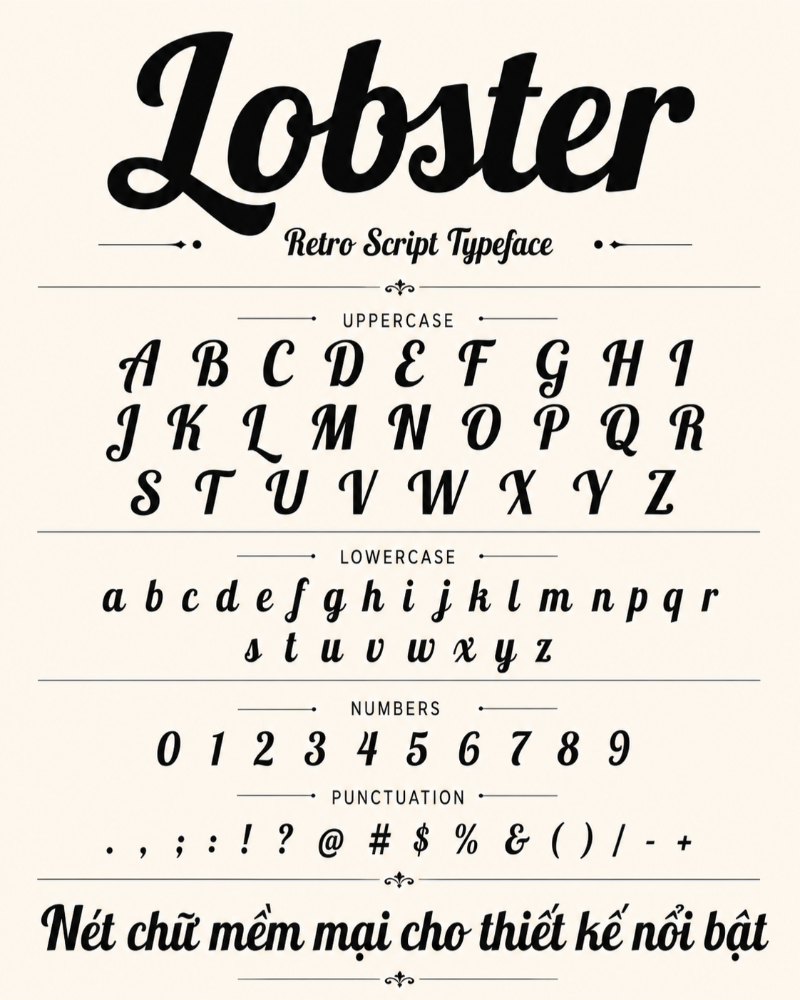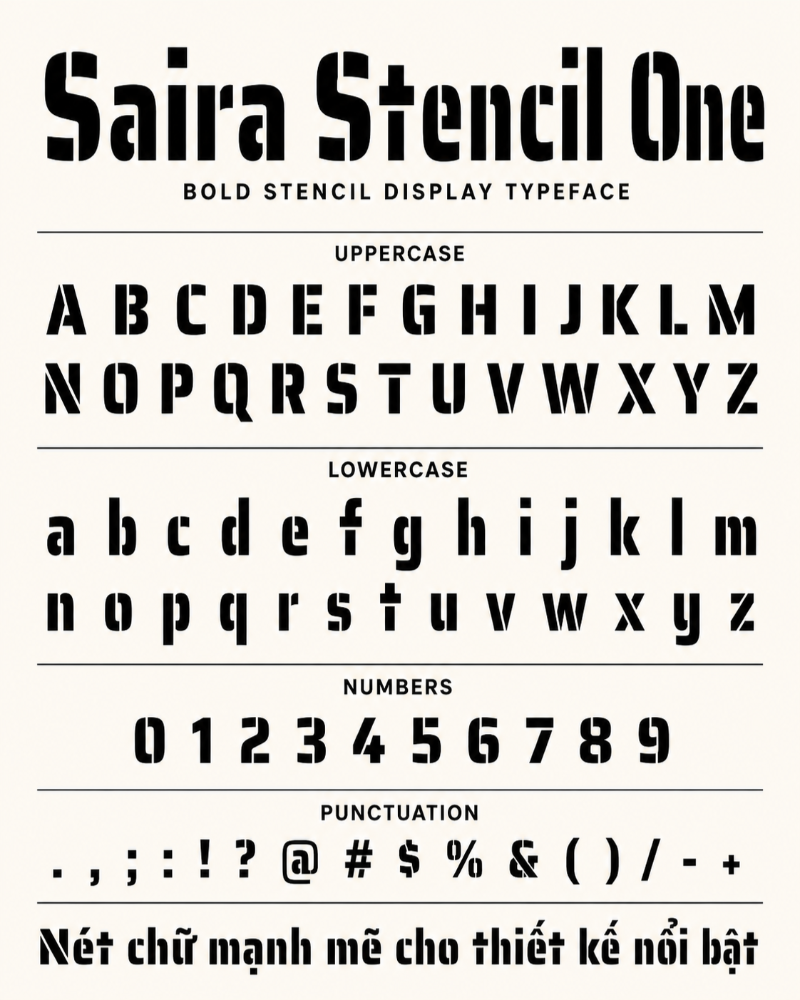
Khi đọc tin tức, lướt mạng xã hội hoặc xem một mẫu banner quảng cáo, yếu tố nào khiến bạn dừng lại lâu hơn? Có thể là hình ảnh bắt mắt, màu sắc nổi bật hoặc một câu thông điệp ấn tượng. Tuy nhiên, thứ thường gây chú ý đầu tiên chính là tiêu đề. Một font chữ tiêu đề đẹp không chỉ làm nội dung nổi bật hơn mà còn giúp thể hiện cá tính, cảm xúc và phong cách riêng của thương hiệu.
Trong bài viết này, In Đại Minh sẽ chia sẻ đến các bạn hơn 12 font chữ tiêu đề đẹp, đã hỗ trợ tiếng Việt, kèm theo những gợi ý ứng dụng thực tế để thiết kế của bạn trông chuyên nghiệp và cuốn hút hơn.
Tại sao một font chữ tiêu đề đẹp lại quan trọng?
Nhiều người mới làm thiết kế thường chọn một font duy nhất cho cả tiêu đề và phần nội dung. Cách làm này có thể khiến bố cục thiếu điểm nhấn, kém chuyên nghiệp và khó thu hút người xem. Thực tế, font tiêu đề đóng vai trò rất lớn trong việc tạo ấn tượng ban đầu.
- Tiêu đề là điểm chạm đầu tiên với người xem: Trong vài giây đầu tiên, người đọc thường nhìn vào tiêu đề trước khi quyết định có tiếp tục xem nội dung hay không. Vì vậy, một font chữ tiêu đề nổi bật sẽ giúp thiết kế gây chú ý nhanh hơn, giữ chân người xem tốt hơn và tăng khả năng truyền tải thông điệp.
- Font tiêu đề và font nội dung có vai trò khác nhau: Font tiêu đề, hay còn gọi là Display Font, cần có cá tính rõ ràng, độ nổi bật cao và khả năng tạo ấn tượng mạnh. Trong khi đó, font dùng cho nội dung chính nên đơn giản, dễ đọc và thoải mái cho mắt khi đọc lâu. Nếu dùng sai vai trò, thiết kế dễ bị rối hoặc thiếu sức hút.
- Font chữ ảnh hưởng đến cảm xúc và nhận diện thương hiệu: Mỗi kiểu chữ đều mang một sắc thái riêng. Font có chân thường tạo cảm giác sang trọng, cổ điển và đáng tin cậy. Font không chân đem lại vẻ hiện đại, gọn gàng và chuyên nghiệp. Còn font viết tay thường gợi sự mềm mại, sáng tạo và giàu cảm xúc. Chọn đúng font tiêu đề sẽ giúp thiết kế truyền tải đúng tinh thần mà thương hiệu hoặc nội dung muốn thể hiện.
Top 12+ font chữ tiêu đề đẹp, việt hóa cho thiết kế 2026
Để bạn dễ chọn font phù hợp với từng kiểu thiết kế, danh sách dưới đây được chia theo phong cách sử dụng và nhóm ngành phổ biến. Mỗi font đều có cá tính riêng, phù hợp cho tiêu đề, banner, poster, bìa tạp chí hoặc các ấn phẩm nhận diện thương hiệu.
Playfair Display
Playfair Display là một font Serif có chân nổi bật, gây ấn tượng nhờ sự tương phản rõ giữa nét mảnh và nét dày. Kiểu chữ này mang lại cảm giác sang trọng, tinh tế và có phần quyền quý. Đây là lựa chọn rất phù hợp cho tiêu đề tạp chí thời trang, banner mỹ phẩm, thương hiệu cao cấp hoặc các thiết kế cần vẻ đẹp thanh lịch.
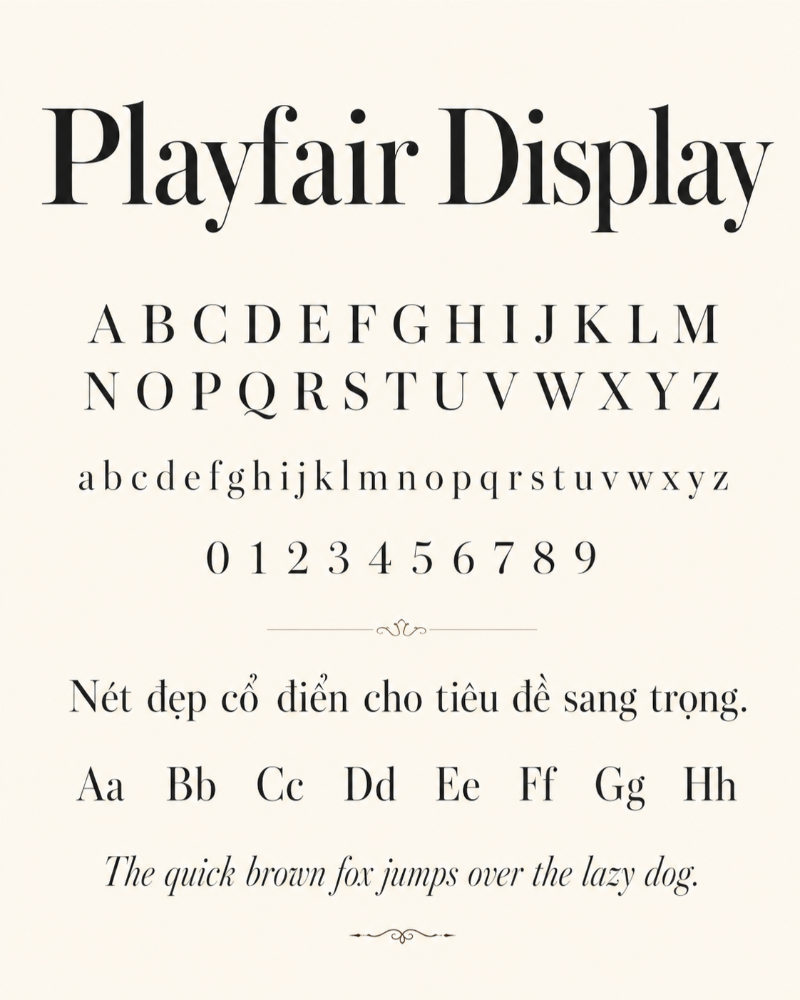
Prata hoặc Yeseva One
Prata và Yeseva One cũng thuộc nhóm font có chân, nhưng đường nét mềm mại và giàu cảm xúc hơn. Hai font này tạo cảm giác nữ tính, trang nhã và quyến rũ, rất hợp với các thiết kế về làm đẹp, spa, thời trang, thiệp cưới hoặc dịch vụ wedding planner. Nếu bạn muốn tiêu đề vừa nổi bật vừa có nét duyên dáng, đây là nhóm font đáng cân nhắc.
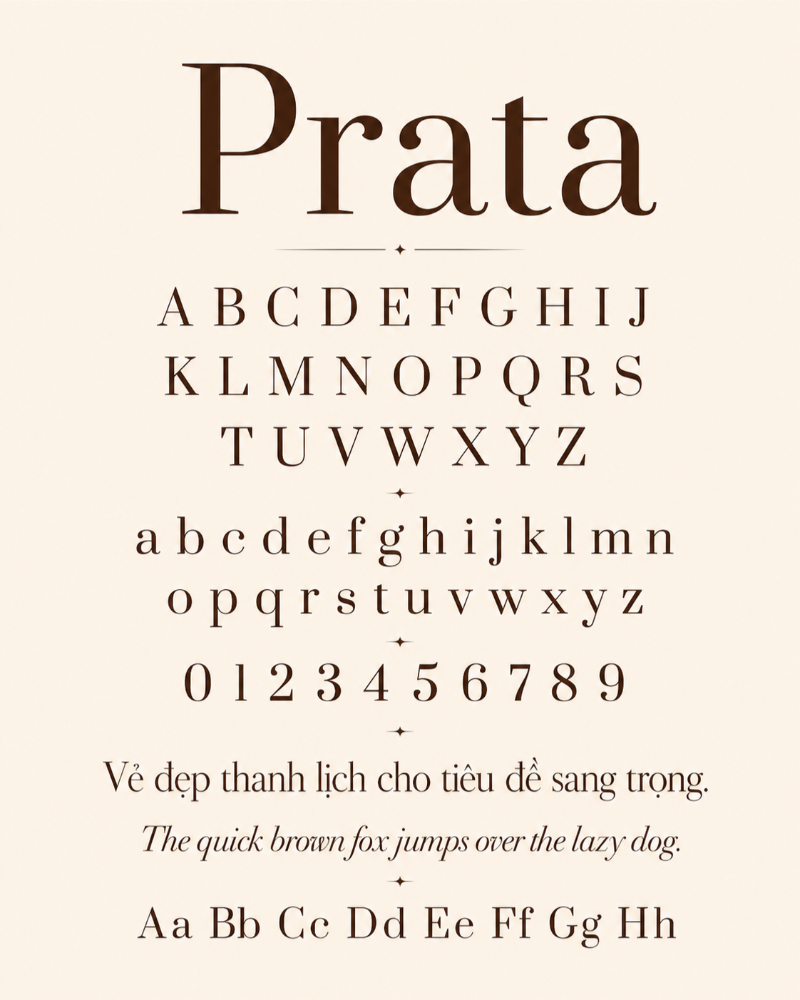
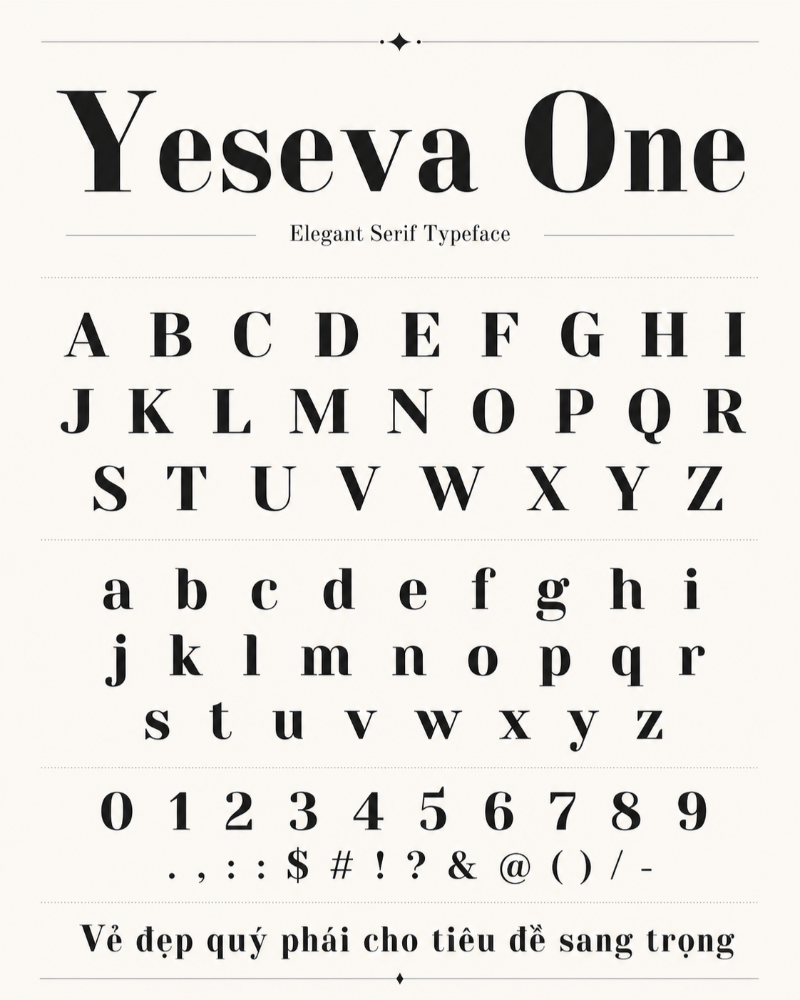
Charmonman
Charmonman mang phong cách thư pháp phương Tây, lấy cảm hứng từ nét chữ viết tay cổ điển. Font này có đường nét bay bổng, mềm mại nhưng không quá rườm rà hay sến. Nhờ vẻ thanh lịch và trang trọng, Charmonman thường được dùng cho thiệp mời, poster sự kiện cao cấp, thiết kế cưới hỏi hoặc các ấn phẩm cần tạo cảm giác tinh tế ngay từ phần tiêu đề.
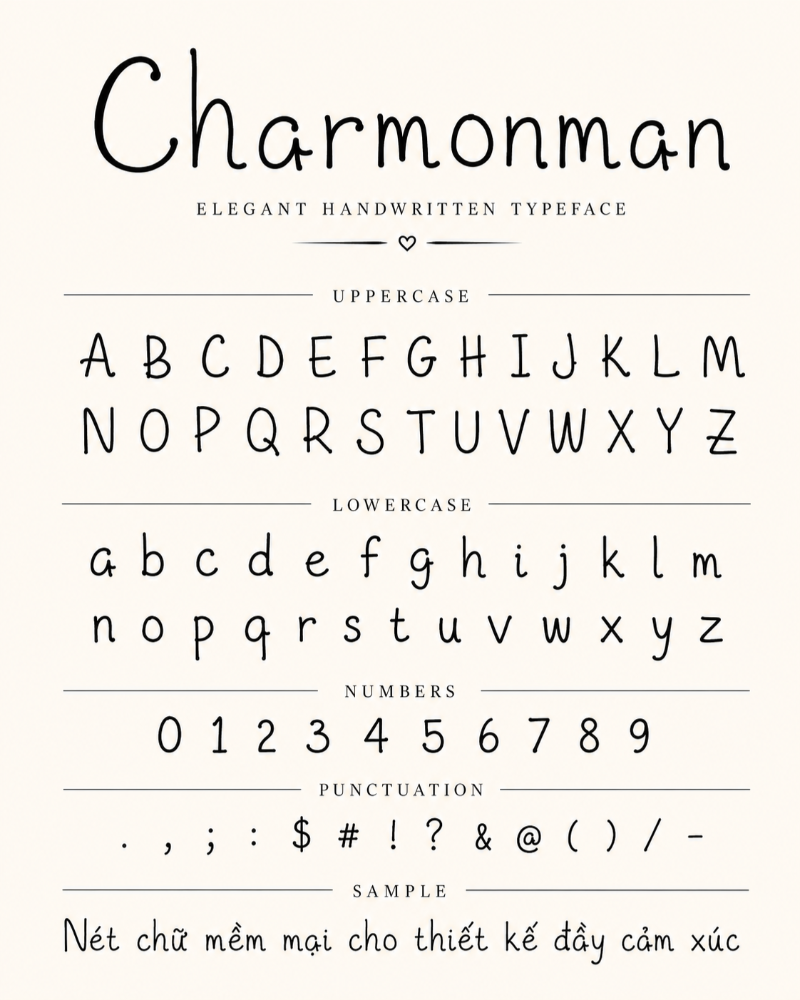
Montserrat Black hoặc ExtraBold
Montserrat được xây dựng dựa trên các đường nét hình học chắc chắn, bố cục chữ rõ ràng và khoảng cách ký tự thoáng. Khi dùng bản Black hoặc ExtraBold, font này tạo cảm giác mạnh mẽ, hiện đại và đáng tin cậy. Đây là một trong những font chữ quen thuộc nhất trong thiết kế UI/UX, nhận diện thương hiệu, logo doanh nghiệp và các tiêu đề cần sự chuyên nghiệp.
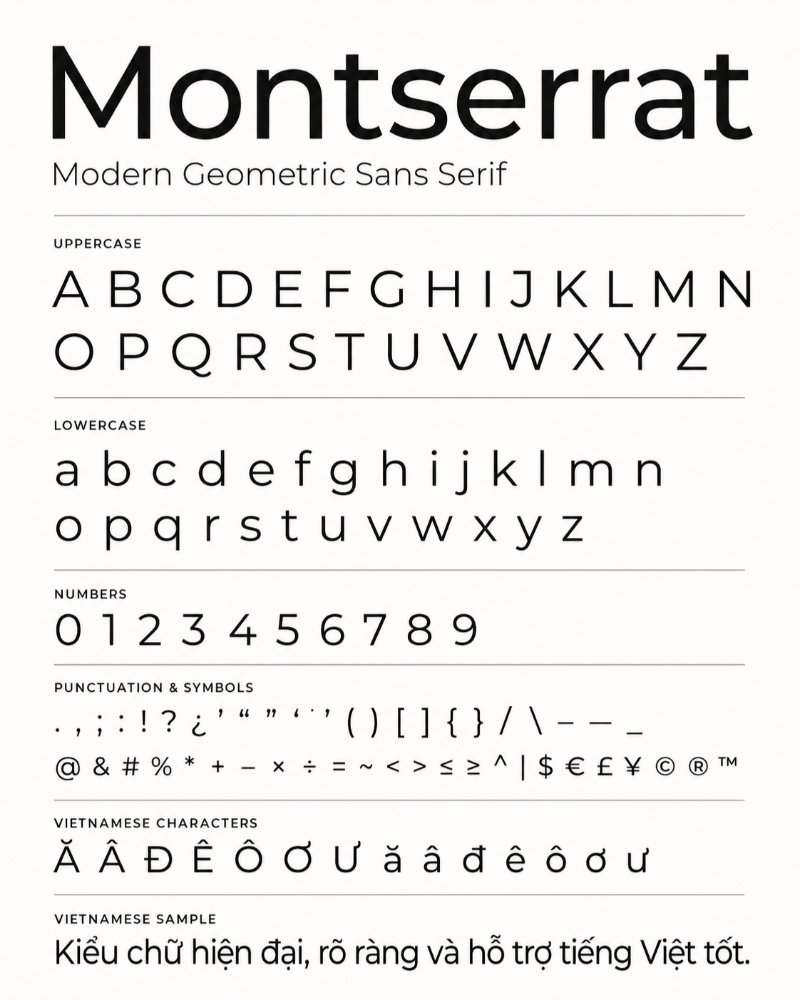
Oswald
Oswald nổi bật với dáng chữ hẹp, cao và gọn. Kiểu chữ condensed này giúp tiết kiệm diện tích ngang rất tốt, đặc biệt khi thiết kế banner, poster hoặc tiêu đề có không gian hạn chế. Dù dáng chữ thon, Oswald vẫn giữ được cảm giác cứng cáp, dứt khoát và dễ tạo điểm nhấn. Font này rất phù hợp cho tiêu đề quảng cáo, headline tin tức hoặc các thiết kế cần sự mạnh mẽ, trực diện.
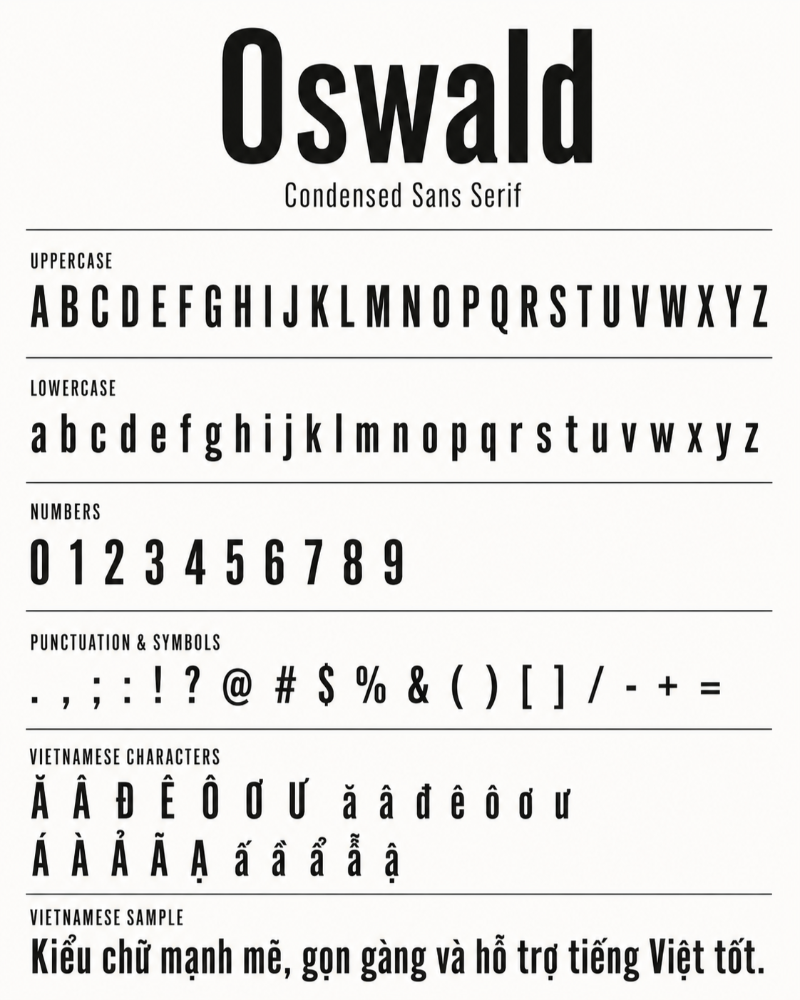
Raleway
Raleway mang vẻ đẹp thanh mảnh, nhẹ nhàng và tinh tế. Điểm nổi bật của font này nằm ở một số ký tự có tạo hình khá đặc biệt, như chữ “W” vắt chéo hoặc chữ “k” được xử lý phá cách. Nhờ phong thái tối giản và hiện đại, Raleway thường được dùng cho tiêu đề phụ, ấn phẩm Minimalist, portfolio, website sáng tạo hoặc các thiết kế cần cảm giác sạch, thoáng và cao cấp.
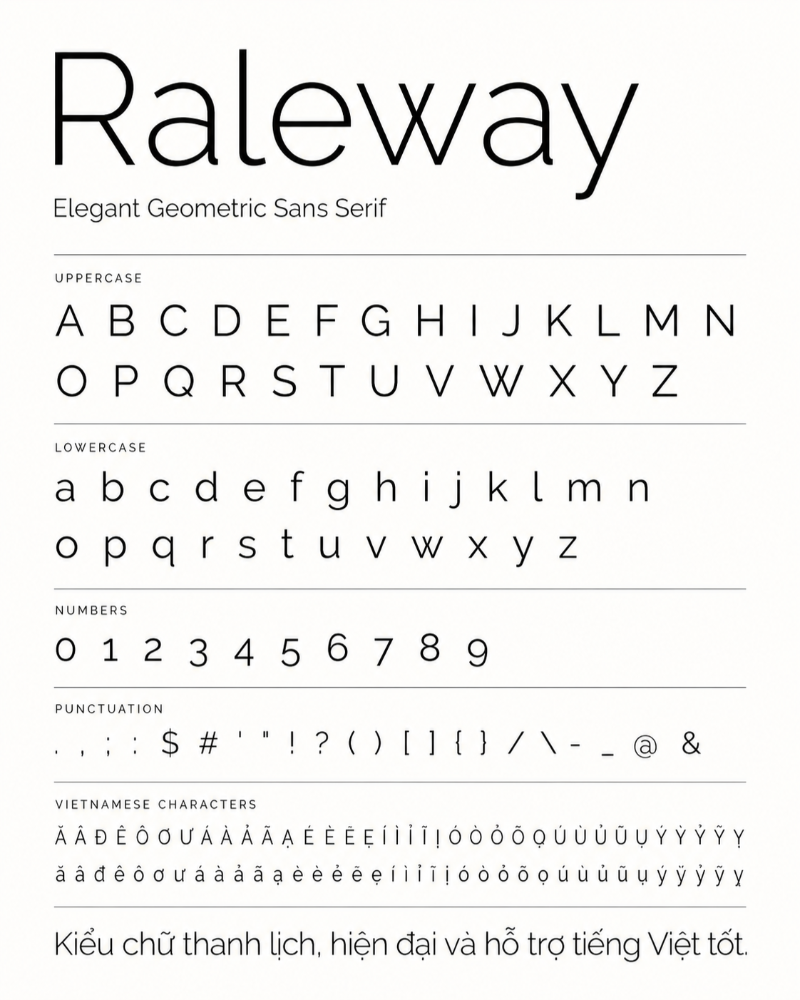
Bangers
Bangers mang rõ tinh thần truyện tranh Comic và Pop-art với nét chữ dày, khỏe và rất bắt mắt. Font này tạo cảm giác vui nhộn, năng động và có khả năng thu hút ánh nhìn gần như ngay lập tức. Vì vậy, Bangers thường được dùng trong poster khuyến mãi, banner YouTube, thiết kế game, thumbnail giải trí hoặc các ấn phẩm cần tạo hiệu ứng nổi bật mạnh.